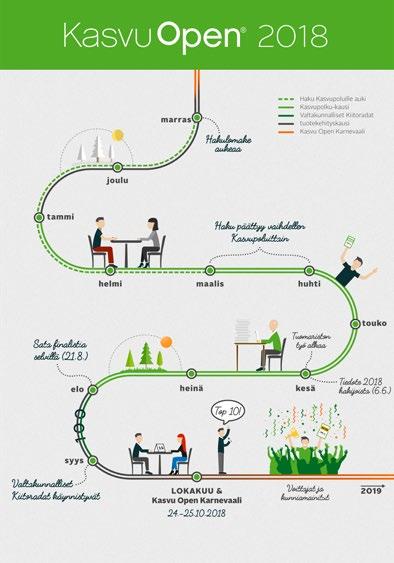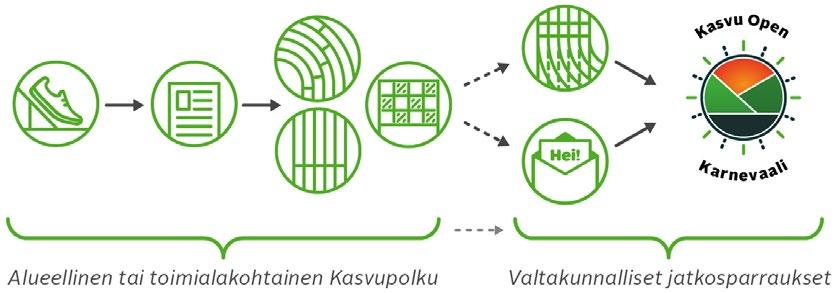
3 JOHDANTO Tervetuloa tutustumaan Kasvu Openin visuaaliseen maailmaan ja graafiseen ohjeistukseen. Kokonaisuutemme koostuu kirkkaasta vihreästä väristä, logosta ja typografiasta. Tämän esityksen tarkoitus on varmistaa Kasvu Openiin liittyvän viestinnän yhtenäisyys ja ohjata niin henkilöstöämme kuin kumppaneitamme materiaalien koostamisessa. Ohjeistuksesta löydät toimintatavat niin logon, värien kuin fonttien suhteen. Seuraamalla tätä ohjeistusta tuotat varmasti brändin mukaista, yksinkertaista ja tyylikästä viestintä- ja markkinointimateriaalia. 3
4 LOGO Kasvu Openin logossa yhdistyvät vihreän värin teemat (s. 6) sekä selkeä ja vahva typografia. Logo on päivittynyt pyöreämpään muotoon vuonna 2018 vanhan logon pohjalta. Logon O-kirjain on hieman muuta tekstiä korkeammalla lennokkuutta, kasvua ja nousua kuvaamassa. Tavaramerkin tunnus on osa logoa, mutta suoja-alueeseen sitä ei tarvitse sisällyttää. Logon värin tulee aina olla joko vihreä tai valkoinen, taustan vallitsevan värin mukaan. Materiaalipankistamme löydät logon kaikki versiot väriprofiileittain. Logoa ei saa koostaa tai jäljentää manuaalisesti tekstinkäsittelytai julkaisuohjelmissa, vaan käytettävä on aina alkuperäisiä logotiedostoja. Vanha logo ( ) Wordilla jäljennetty 4
5 TYPOGRAFIA Typografia on merkittävässä roolissa Kasvu Openin brändin viestinnässä. Kasvu Openin fontti kaikissa materiaalissa verkkosivujamme lukuunottamatta on Alright Sans. Isot otsikot: ULTRA, mieluiten kapiteeli- eli isoin kirjaimin. Ingressit: MEDIUM ITALIC. Myös tässä suositaan isoja kirjaimia. Leipäteksti: Light (myös Regularin käyttö on mahdollista jos Lightleikkaus syystä tai toisesta ei sovi julkaisuun) Yksittäisiin korostuksiin, huudahduksiin tai iskulauseisiin käytetään käsinkirjoitettua muistiinpanoa muistuttavaa Fabfelt Script -kirjasimen Bold-leikkausta. Pitkissä nostoissa tai esimerkiksi ingresseissä Fabfeltista voi tulla vaikealukuinen käytä maalaisjärkeäsi! Tekstinkäsittely- ja taitto-ohjelmissa joissa se on mahdollista (kuten Indesignissa), on suositeltavaa käyttää Alright Sansin OpenType-määritteissä Proportional Lining (suomeksi Suhteutetut viivat) -asetusta. Tällöin käytössä ovat täysikorkuiset numerot. Vertaa ja Tämä on huudahdus! Fabfelt Script abcdefghijklmnopqrstuvwxyzåäö 5
6 VÄRIT Kasvu Openin pääväri valkoisen ohella on kirkas vihreä #4FAB24, joka kuvastaa sparrausohjelman pääteemoja: kasvua, uudistumista ja verkostoa. LISÄVÄRI R0 G109 B37 #006D25 C75 M0 Y100 K36 PMS 7733C PMS 356U Brändin lisä- ja huomiovärinä on tumma vihreä #006D25 ja tehosteissa voidaan käyttää harmaata # TEHOSTE R69 G69 B69 # C10 M10 Y10 K80 KARNEVAALI R69 G69 B69 # C10 M10 Y10 K80 R238 G51 B17 #EE3311 C0 M80 Y90 K10 6
7 MUUT GRAAFISET ELEMENTIT 1/2 Kasvu Openilla ei ole logon lisäksi varsinaista liikemerkkiä, mutta logon tueksi voi sekalaisiin materiaaleihin upottaa tällä sivulla esitettyjä graafisia elementtejä, mukaanlukien kaudella 2017 käyttöön otettuja leimasimia ja piktogrammeja. Kasvupolkurakenteelle on luotu omat piktogrammit, mutta myös muiden piktogrammien käyttö on sallittu kunhan ne noudattavat tyyliltään Kasvu Openin omia, ohessa näkyviä malleja. Vanha yksinkertainen on kaunista -sanonta pätee meilläkin! Tämän sivun elementtejä voi käyttää kaikissa Kasvu Openin väreissä. Kehys nostoihin! Hakuvaihe Kasvupolku -startti / Kiitoradat Kasvupolun semifinaali Kasvupaja 7
8 MUUT GRAAFISET ELEMENTIT 2/2 Kasvu Openin prosessi voi monimuotoisuutensa puolesta olla monelle olla ensi kuulemalta haastava sisäistää. Tätä varten olemme luoneet erilaisilla graafisilla elementeillä varustettuja infograafeja kokonaisuuden avaamisen helpottamiseksi. Sivun materiaalien pääasiallinen käyttö on Kasvu Openin nettisivuilla sekä kumppaneille suunnatuissa viestintä- ja ohjeistuspaketeissa, mutta verkostoon kuuluvat voivat halutessaan ladata kuvat materiaalipankistamme ja jakaa sieltä eteenpäin. 8
9 KUVAT & VÄRIT Hyvä tapa tehdä Kasvu Open -materiaaleista Kasvu Openin näköisiä on luoda kuvitusten päälle vihreä väripeitto. Jos käytössäsi on Adobe Photoshop, saat tehtyä väripeiton helposti kahdellakin eri tavalla: vaihtoehto 1, kirkkaampi (suositus!) Luo valitsemasi kuvan päälle uusi taso (layer) ja täytä se Kasvu Open -vihreällä Aseta väritason sekoitustilaksi Color/Väri Säädä alemman kuvatason läpinäkyvyyttä (Opacity) sopivaksi (esim. 35 %:sta on hyvä aloittaa!) vaihtoehto 2, tummempi Luo Photoshopissa valitsemasi kuvan alle uusi taso (layer) ja täytä se Kasvu Open -vihreällä Aseta kuvatason sekoitustilaksi (Blending Mode) Multiply (suomeksi Kertova) Säädä kuvatason läpinäkyvyys (Opacity) sopivaksi (esim. 50 %:sta on hyvä aloittaa!) Verkkosivukäytössä kuvia voi värjätä luomalla kuvan päälle värialueen jonka taustaväri asetetaan RGBA-muotoon (alpha channel). Kasvu Openin nettisivuilla alpha-kanavan arvo on 0.75, eli kuvan läpinäkyvyys on 75%. Esimerkkejä värien käytöstä taustoissa ja väripeittoina. Värien käyttöä materiaaleissa on hyvä jakaa näin: vihreä 60 % vihreä 20 % harmaa 20 % Kasvu Openin kaksi vihreää väriä voi myös yhdistää liukuväriksi kuvia varten. #4FAB24 #006D25 9